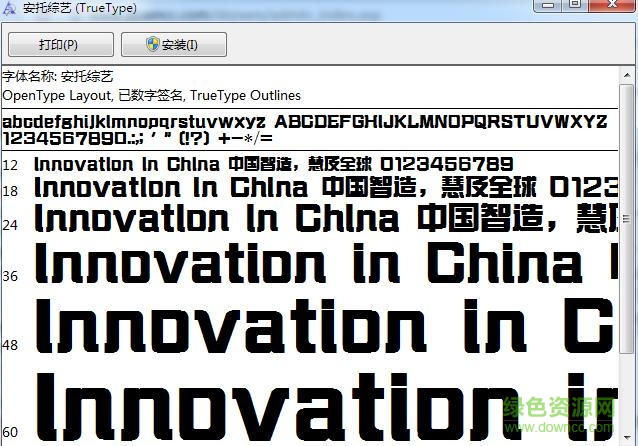
安托綜藝體
安托綜藝字體是一款看上去非常醒目的中文字體,具有整齊、雄壯、厚重的特色,整體看上去非常的美觀,有需要的朋友歡迎下載使用!
安托綜藝字體簡介
安托綜藝字體是一款字形非常有特色的綜藝字體,以黑體為基本出發(fā)點,外觀更趨方正,外張,結(jié)構(gòu)與筆劃更善于平均分布,擺脫了傳統(tǒng)黑體之規(guī)范,更具自由,適用于一般海報,報紙,雜志標題!